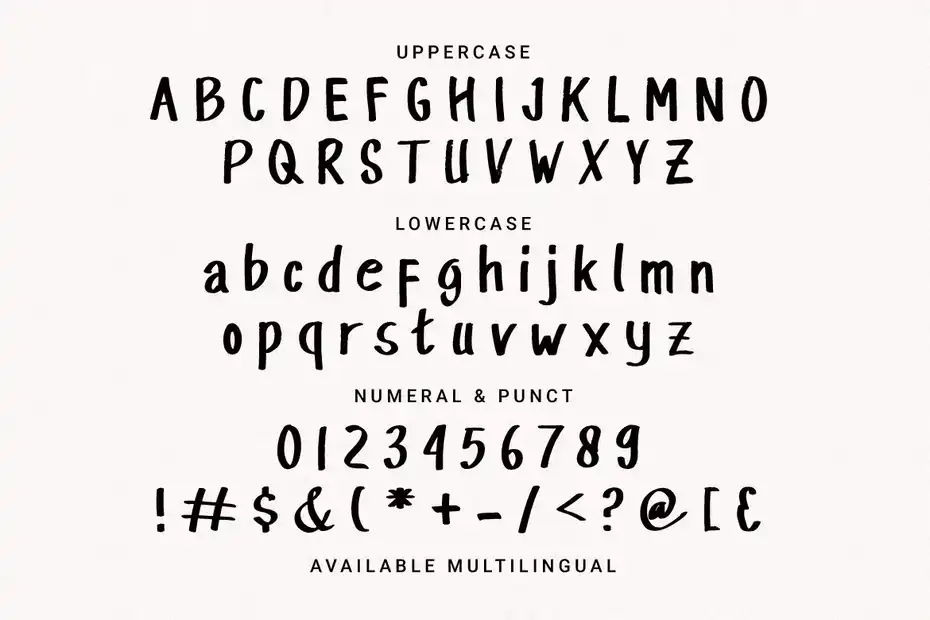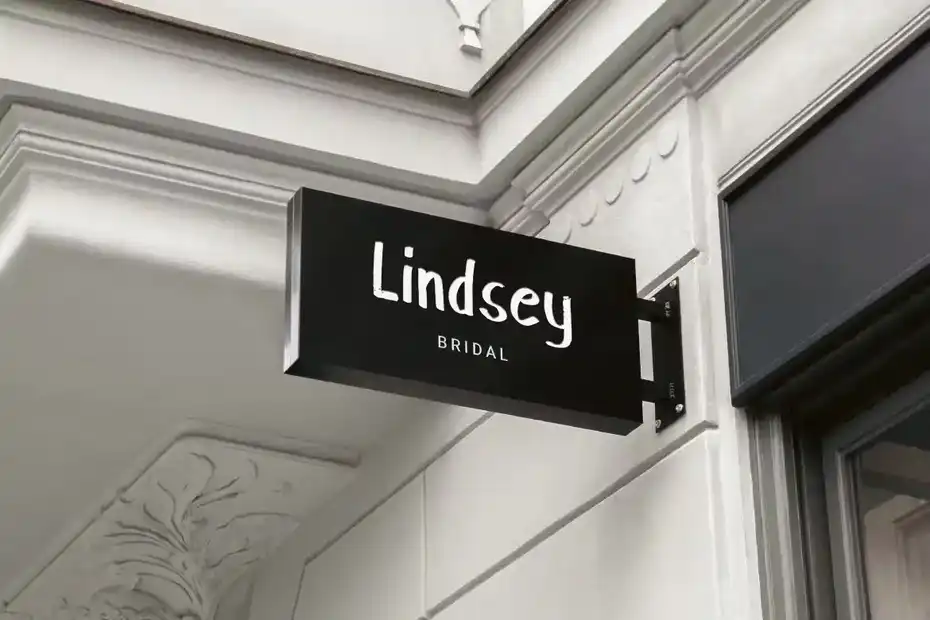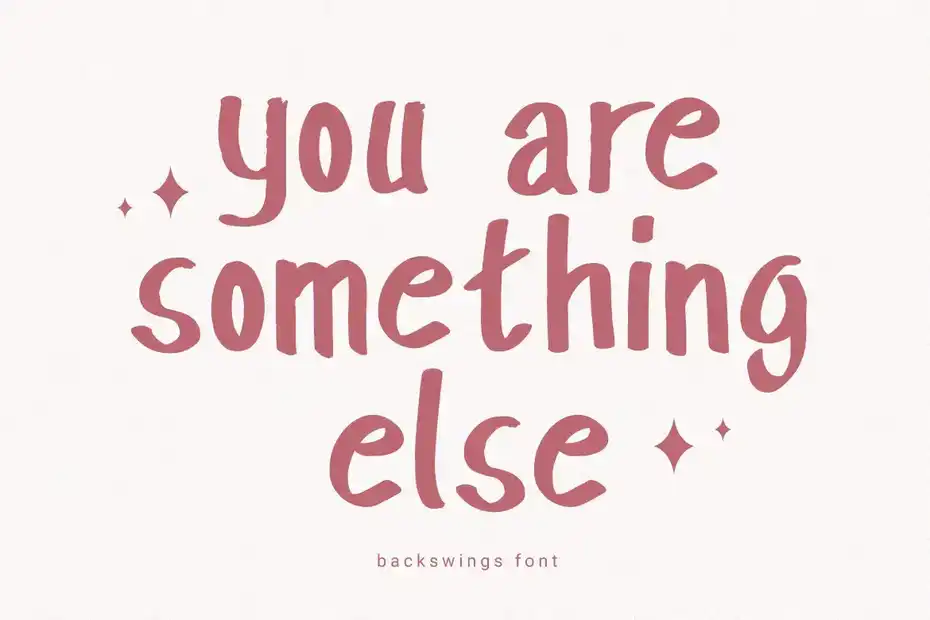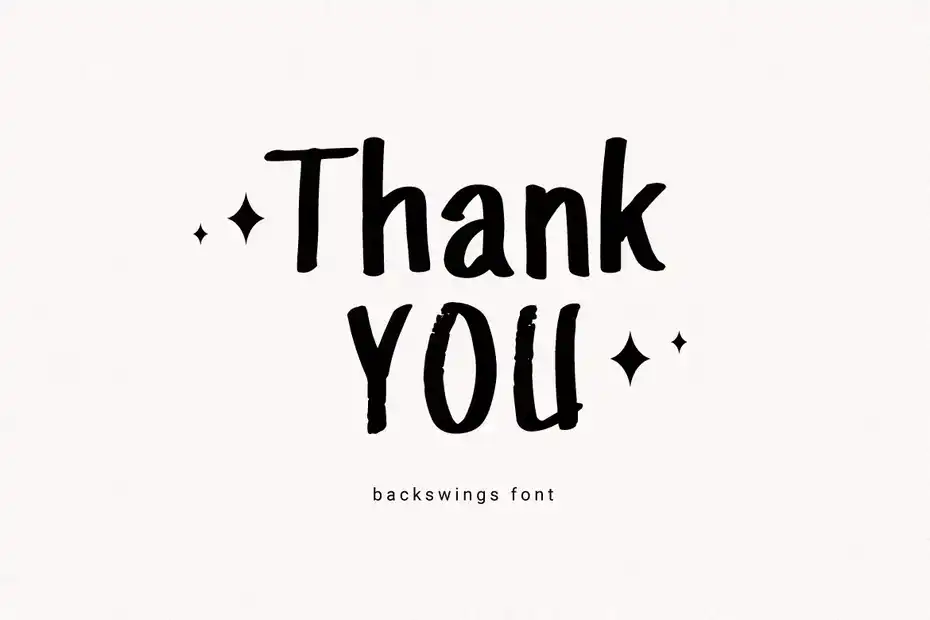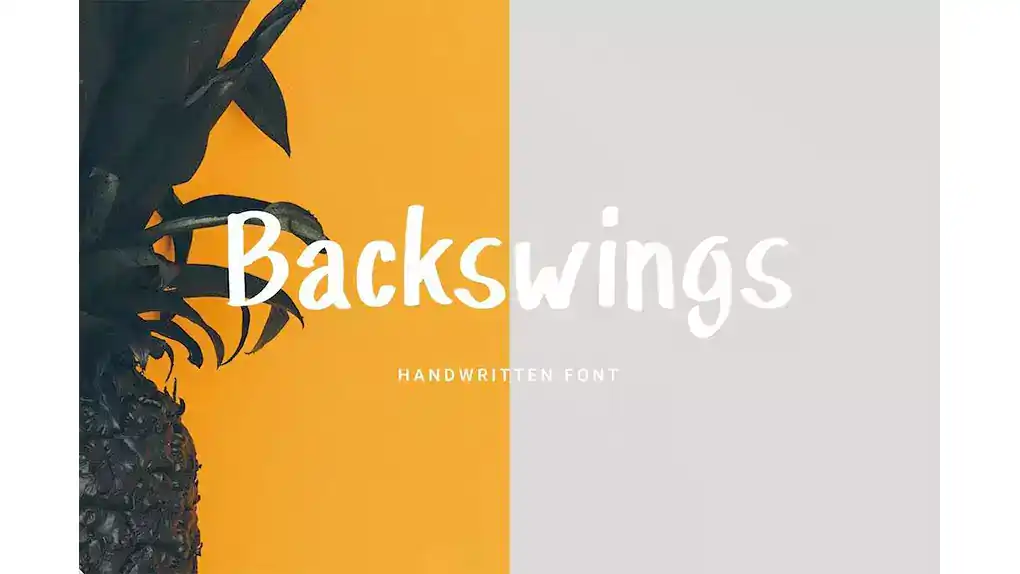
فونت انگلیسی Backswings – Handwritten Display Font : این مجموعه شامل یک فونت دست نویس است که برای کالا، نقل قول، پست شبکه های اجتماعی و غیره مناسب میباشد.